Мелкий шрифт и приложения. На какие уловки шли издатели газет прошлых веков
Вообще обычный горожанин редко задумывается, какие сокровища хранит отдел газет РНБ, с давних пор занимающий больше половины здания на набережной реки Фонтанки, 36. Что касается дореволюционной периодики — тут практически вся «география» Российской империи: от Владивостока до Варшавы. Есть газеты белого движения, русской эмиграции, даже гитлеровской Германии, есть издания, выходившие во время войны на оккупированной территории.
— Мы храним не только газеты.
В наших фондах — сплетенные в огромные тома афиши Петербурга, Москвы, Вильны и некоторых провинциальных городов: все они датированы второй половиной XIX — началом ХХ века
Вместе с Марией Луковской мы идем по фондам отдела. На стеллажах — тяжеленные подшивки в кожаных переплетах, которым зачастую уже почти по полтора века.
— Первые газеты выходили в книжном формате, — показывает Луковская переплеты «Санкт-Петербургских ведомостей» XVIII века. — Затем появился привычный нам сегодня широкий формат. Причем он был даже больше нынешнего.
Самые большие по размеру газеты выходили во Владивостоке и Одессе: портовые города раньше других приобретали иностранное печатное оборудование, а поскольку за рубежом налоги рассчитывали из количества страниц, то и типографские станки были рассчитаны на максимально большой формат листа.
Логика проста: чем меньше страниц в газете, тем меньше надо заплатить налогов.
— Соответственно, и шрифт был очень мелкий, чтобы влезло как можно больше, — поясняет Луковская. — В русских газетах он еще приемлемый, а британскую The Times середины XIX века без лупы вообще читать невозможно. Наверное, у англичан было очень острое зрение…
Как газеты выживали, чем зарабатывали на жизнь? Частные издания (а таких было большинство) жили с подписки, розничной продажи и рекламы. «Санкт-Петербургские ведомости» были государственными: редактора нанимали. Если его работа не нравилась, увольняли и брали другого. Долгое время газета получала доход с казенных объявлений.
Можно ли было разбогатеть на газетном бизнесе? Вполне. Офицер Комаров, понимавший толк в журналистике (он был корреспондентом во время Русско-турецкой войны), основал в Петербурге газету «Свет» и весьма преуспел. Приобрел типографию, печатал книги.
Другой рецепт успеха: к сотрудничеству приглашали, как бы мы сегодня сказали, раскрученных медийных персон. Именно так, к примеру, поступил редактор «Русской газеты», позвавший в нее в 1905 году Льва Троцкого. И не прогадал: с 40 тысяч экземпляров тираж взлетел сразу же до 120 тысяч. Мог бы, наверное, и до полумиллиона, но типографских мощностей не хватало… Правда, газету вскоре закрыли…
Вообще же газет было много, они яростно конкурировали между собой — оперативностью и качеством информации, а также всевозможными приложениями. Например, «парижскими модами» с выкройками и узорами.
Кстати, в «Санкт-Петербургских ведомостях» иллюстрации в приложениях появились еще в 1733 году. И самая первая — к статье «О морских червях». Впоследствии печатали чертежи, планы и карты к сообщениям о новинках науки и исторических событиях, преимущественно военных.
На многих переплетах в газетном хранилище — указание: «По ветхости не выдавать».
Раз так, выход один: предоставлять читателям оцифрованные версии. И действительно, многие петроградские газеты того времени уже отсканированы, они доступны на интернет-сайте РНБ.
— С оцифровкой изданий других лет дело обстоит гораздо хуже, — признается заведующий отделом газет Александр Сапожников. —
И совсем будет хорошо, если подобную программу пропишут отдельной строкой в государственном бюджете. Именно так происходило во многих европейских странах.
Пока же читатели в основном работают с газетами по старинке — с бумажными экземплярами или микрофильмами. Правда, если раньше приходилось кропотливо делать выписки, то теперь разрешено пользоваться собственной «фототехникой» (только без вспышки), включая встроенные фотокамеры телефонов. Так что теперь даже смысла нет вырезать что-то из газет, чем, увы, грешили читатели прошлых лет.
— Больше всего пострадали в 1990-х годах иностранные спортивные газеты. Тогда была викторина с солидными призами, и читатели искали ответы на вопросы. Соперничая, они удаляли информацию, чтобы помешать конкурентам. Впрочем, и до революции с газетами не церемонились. У нас есть московская «Ремесленная газета» с вырезанными иллюстрациями, — говорит Мария Луковская.
Какие газеты сегодня наиболее востребованы? Предпочтения читателей меняются.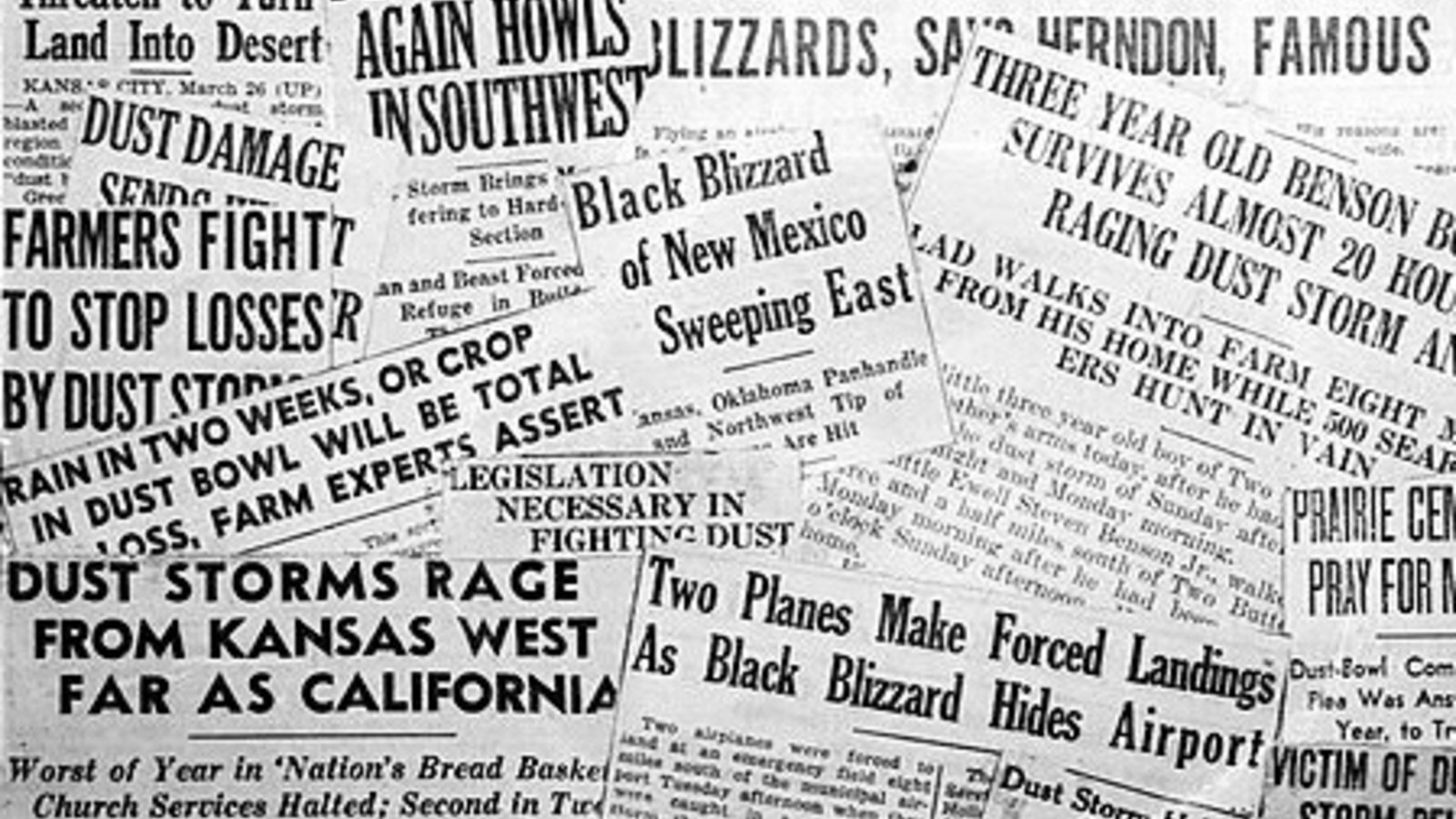
И, наконец, о наболевшем: есть ли будущее у бумажной прессы?